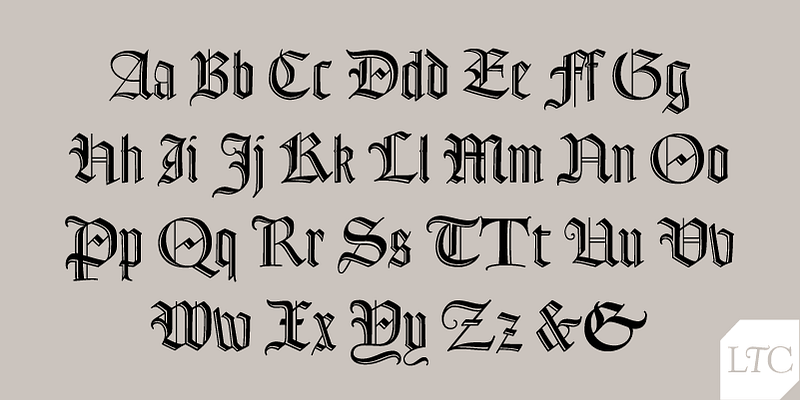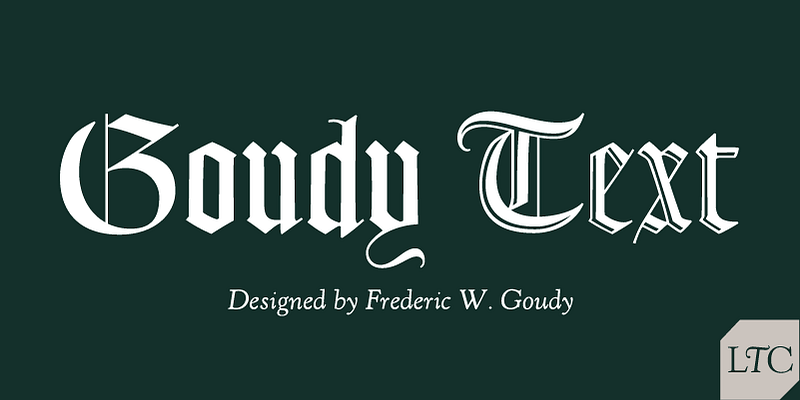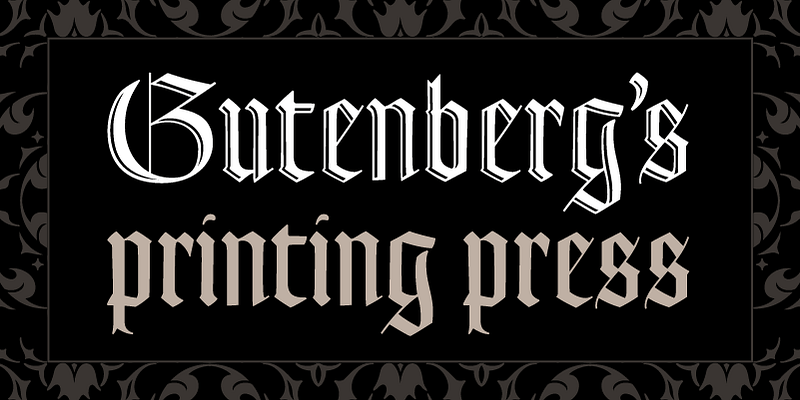
LTC Goudy Text ist eine gotische Schrift, die 1928 von Frederic Goudy entworfen wurde und auf der Gutenberg-Bibel (42 Zeilen) basiert. Die Goudy Text Shaded ist eine Inline-Display-Variante, die später von Lanston Monotype als dekorative Lombardic Titling Caps hinzugefügt wurde, um die Goudy Text zu ergänzen und ihr eine unverwechselbare historische Note zu verleihen. Ein vollständiger Satz von Kleinbuchstaben sowie einige zweckmäßige Ligaturen und Alternativzeichen wurden hinzugefügt. Die Schrift hat einen klaren Bezug zur Vergangenheit und wirkt heute etwas unkonventionell.